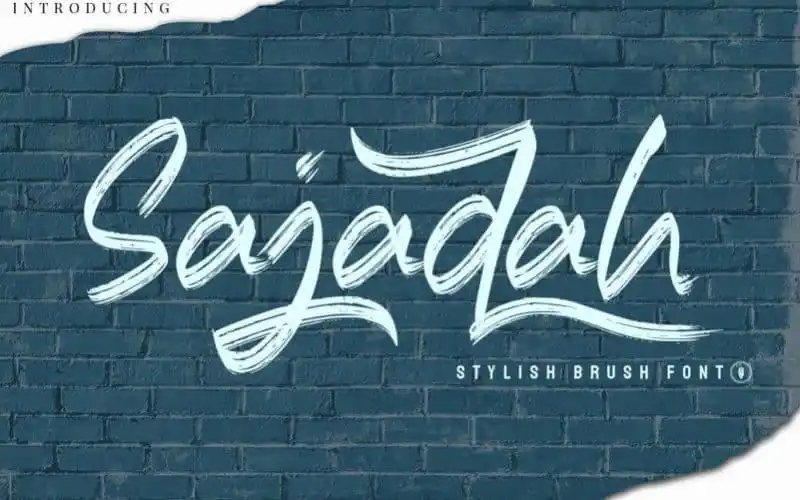
Sajadah Brush Font – Download Grátis
A Sajadah Brush Font é uma hermosa tipografia que flui com elegância, criada a partir de traçados manualizados com auxílio de um pincel. Essa fonte se destina a qualquer projeto, seja para logotipos e projetos de marca, decorações de casa, embalagens de produtos, têis, ilustrações, materiais de presentes, envelopes, cartas de cumprimentos, etiquetas, fotografia ou assinaturas de eventos especiais. Ela oferece um toque delicado e encantador, perfeita para projetos que buscam uma sensação agradável e especial. Seja para criar identidades visuais memoráveis, arte decorativa em casa, designs práticos como embalagens ou até mesmo roupas personalizadas, a Sajadah Brush Font é sua aliada ideal.